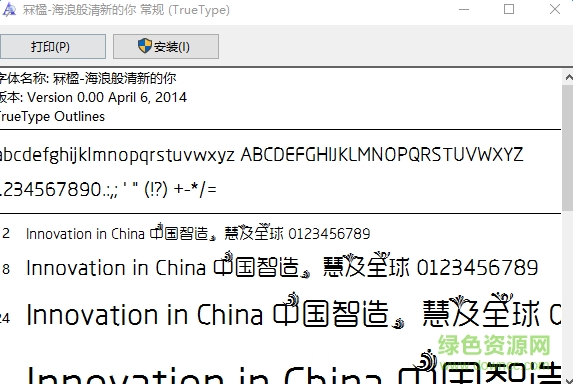
海浪般清新的你字體是一種很不錯的電腦藝術(shù)字體,這款字體最大的特點就是寫出來的字上面會有海浪一樣的裝飾物品,是不是很好看很有趣呢,喜歡的朋友就快來綠色資源網(wǎng)下載吧。
海浪般清新的你字體是一款很有特色的電腦字體,很多年輕人也都是很喜歡這種有特色的字體的,因為寫出來的字會很好看,很有個性,大家如果喜歡的話可以隨時來綠色資源網(wǎng)下載。